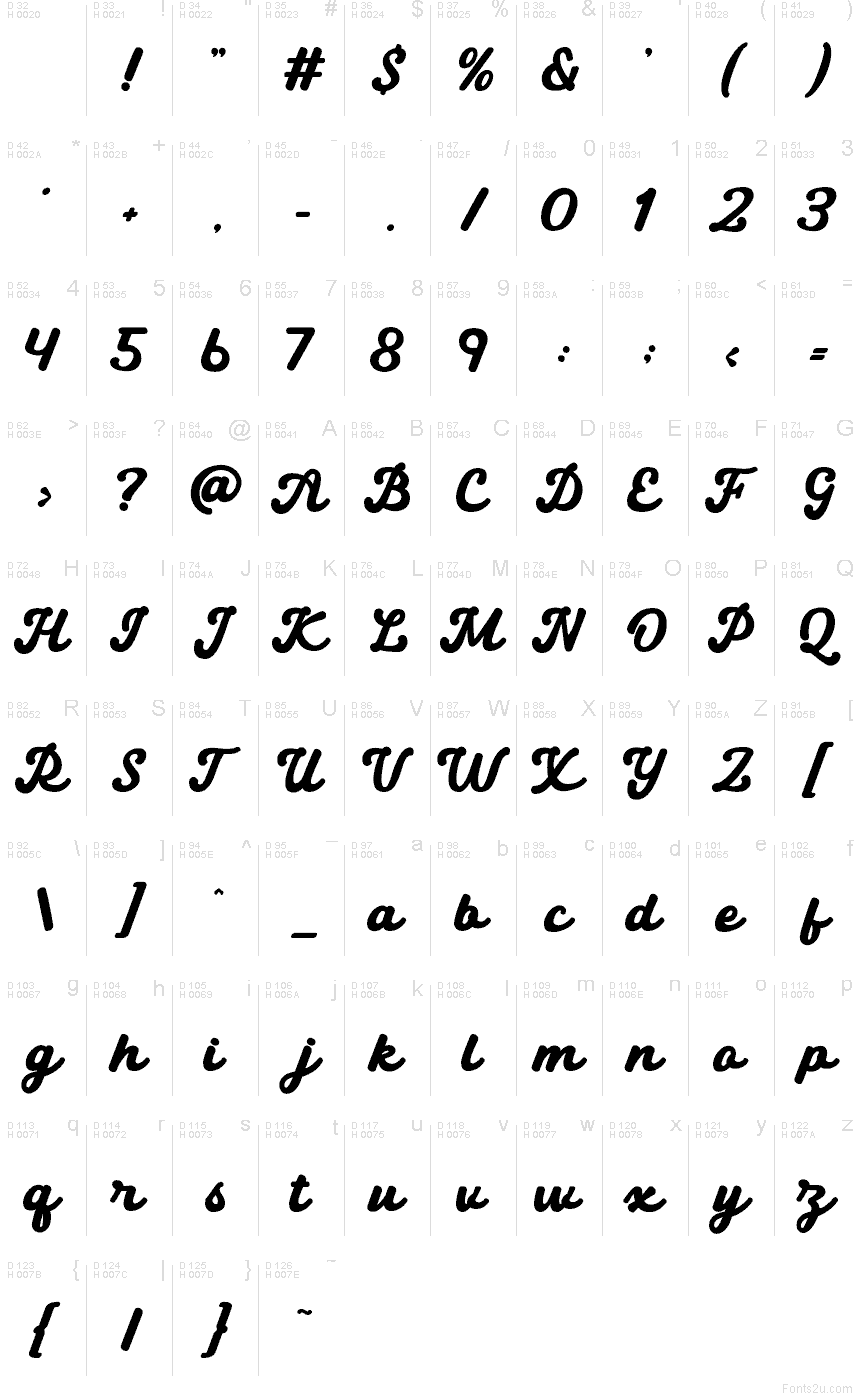
Locke Port de Putracetol Studio est une police brush script gratuite aux traits larges, généreusement encrés, et au tracé fluide et plein d'élan. Des boucles arrondies et des liaisons délicatement pincées apportent de la vivacité au lettrage. Les grandes capitales s'élèvent nettement au-dessus des bas-de-casse plus amples.
Les marques liées à l'univers de la musique, du streetwear ou de la restauration décontractée peuvent tirer parti de son élan assuré pour des logos et des emballages. Elle convient également aux affiches d'événements et aux produits dérivés. Ses traits bouclés peuvent faire écho à des illustrations faites à la main, intégrant ainsi le lettrage à l'œuvre elle-même.